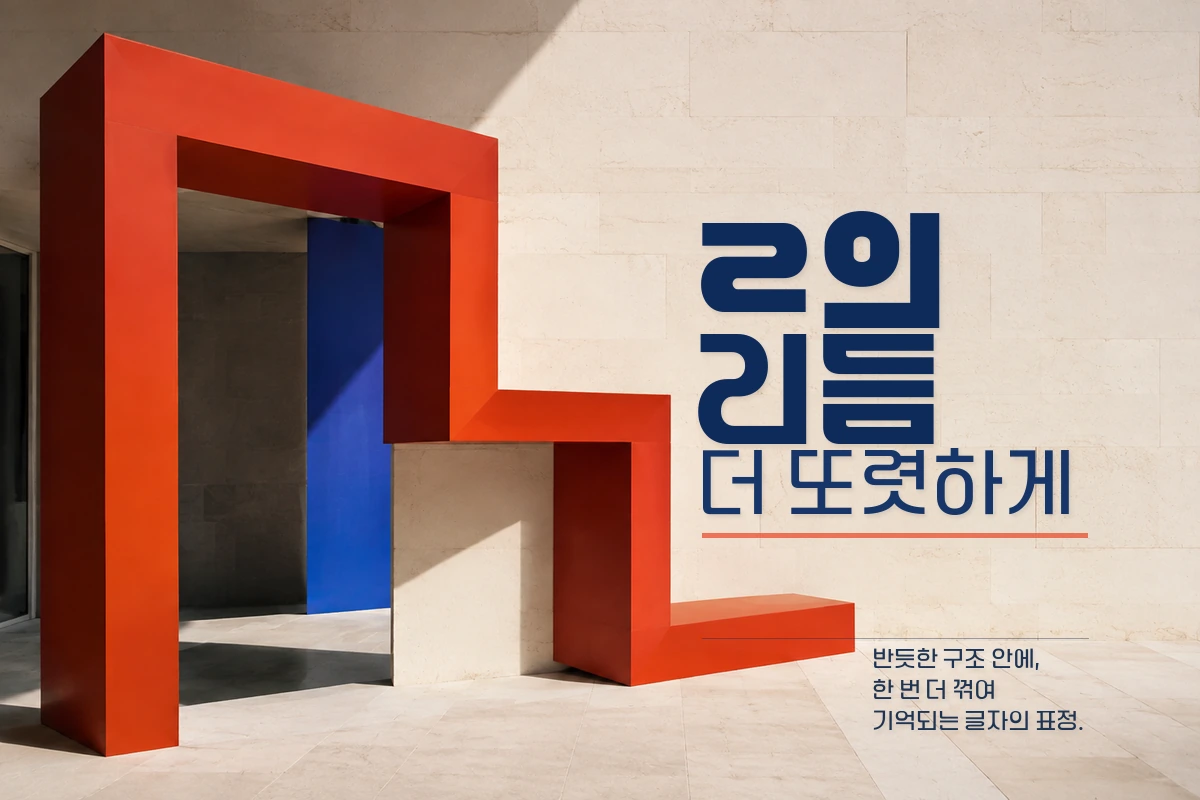
리아체 — 롯데리아에서 배포하는 무료 폰트입니다. 반듯한 고딕 구조에 독특한 ‘ㄹ’ 조형을 더해 선명한 개성을 보여주는 브랜드 서체
롯데GRS의 디자인센터가 티티서울과 함께 기획해 만든 롯데리아의 전용 서체입니다. 이름은 롯데리아의 리아에서 왔습니다. 가장 굵은 Extra Bold가 먼저 나왔고 나중에 Bold와 Regular가 더해져 세 굵기가 됐습니다.
한글 조형의 아름다움을 정직하면서도 정제된 형태로 전한다는 것이 제작 의도로 소개됩니다. 파일에서 재어 보면 자면을 넉넉히 채운 굵은 고딕이라 패키지나 매장 사인처럼 멀리서 읽는 자리에 맞습니다.
굵기가 셋이라 제목과 본문을 나눠 쓸 수 있는 것이 장점입니다. 다만 라이선스에 제한이 있어 회사명이나 로고 같은 BI와 CI에는 쓸 수 없고, 폰트를 수정하거나 다시 배포하는 것도 금지됩니다.